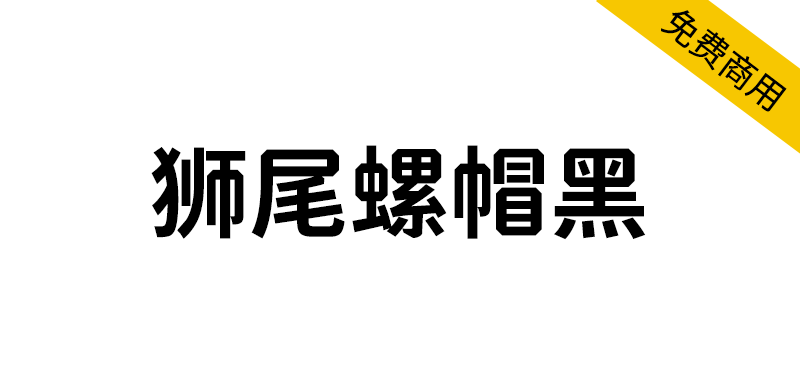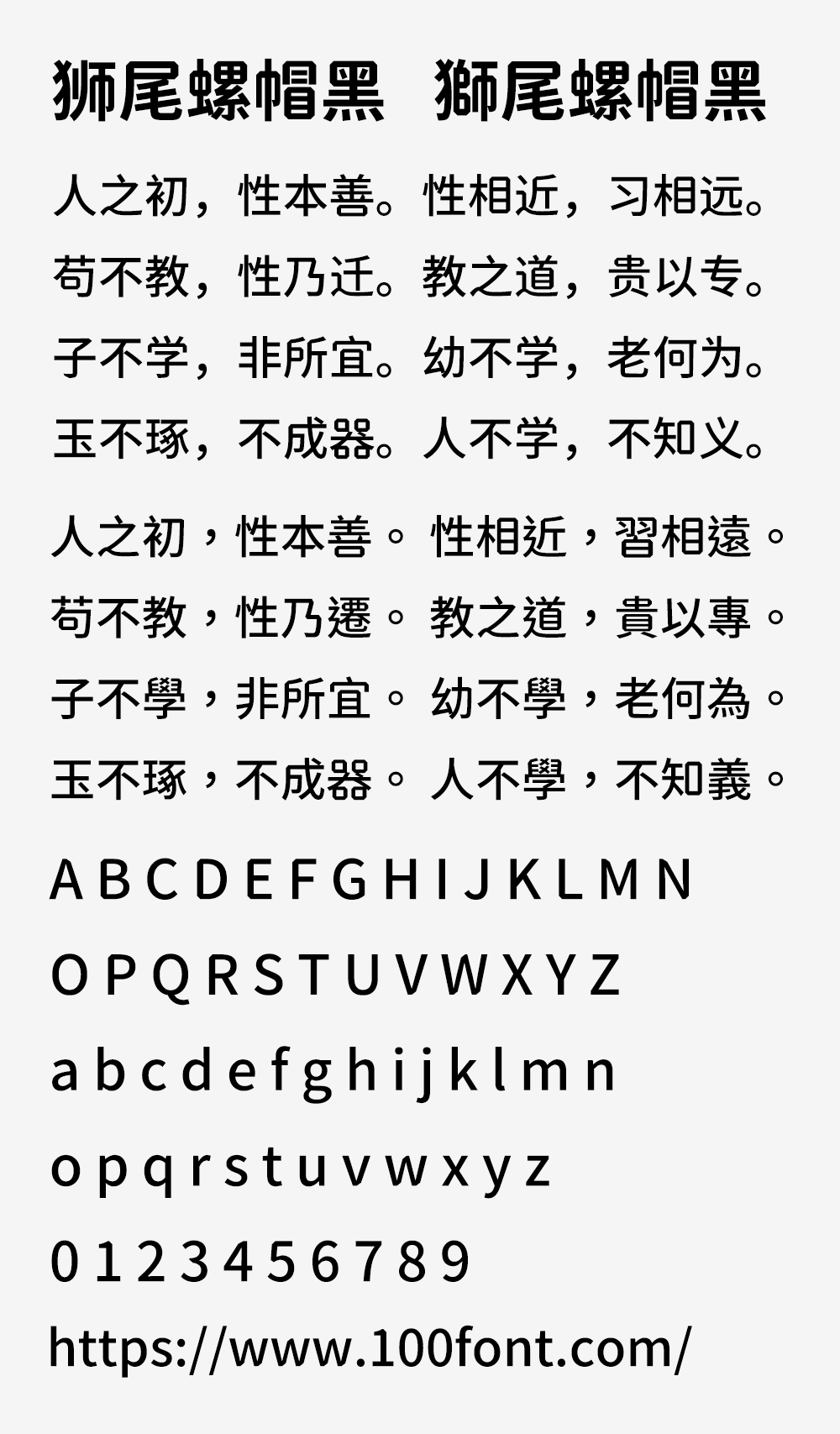
狮尾螺帽黑基于思源黑体增加斜角和拔脚改造,更加简明现代化的字体。狮尾螺帽黑体的特色是「口」字的转角处增加一个斜角,外形有点像螺帽。和思源黑体一样,有7种字重,支持简体中文、繁体中文、韩文与日文,可以免费商用,欢迎大家自由应用、自由优化、自由改作!
狮尾螺帽黑和「狮尾螺帽腿黑」差别在有没有拔脚,「拔脚」就是会有较少的笔画,例如移除「口」字的左右下角会多出的短线条。有拔脚的字会较圆,但是会造成有些字因直接去掉腿后左右不平衡、左右不对衬的「悬空」问题。改使用「腿」系列字体就不会有这个问题。